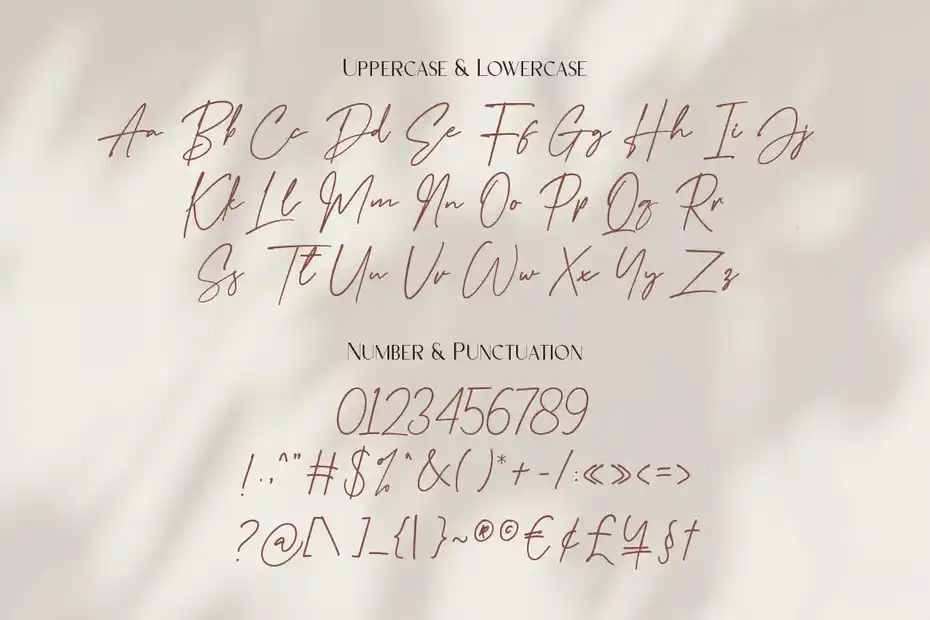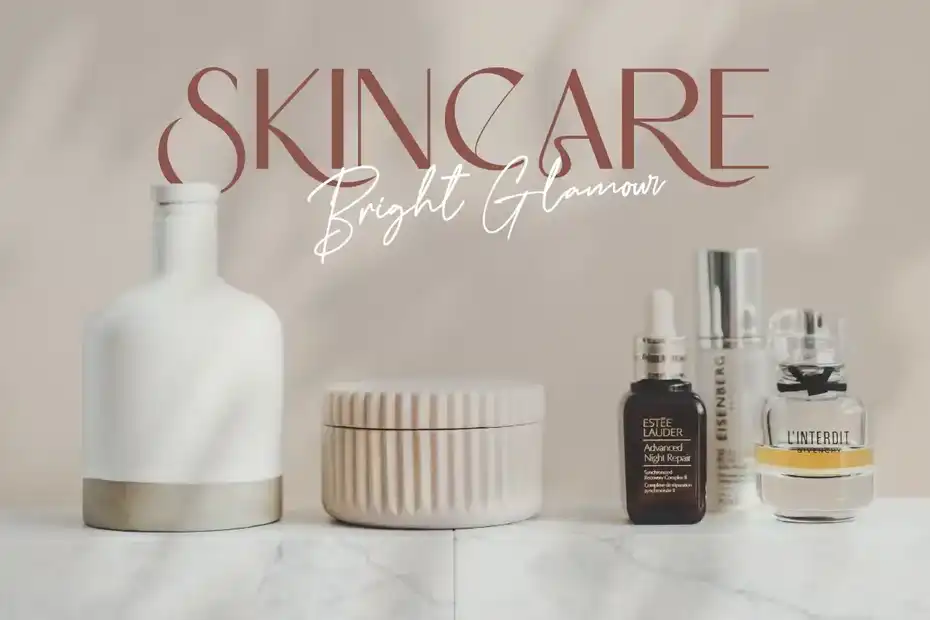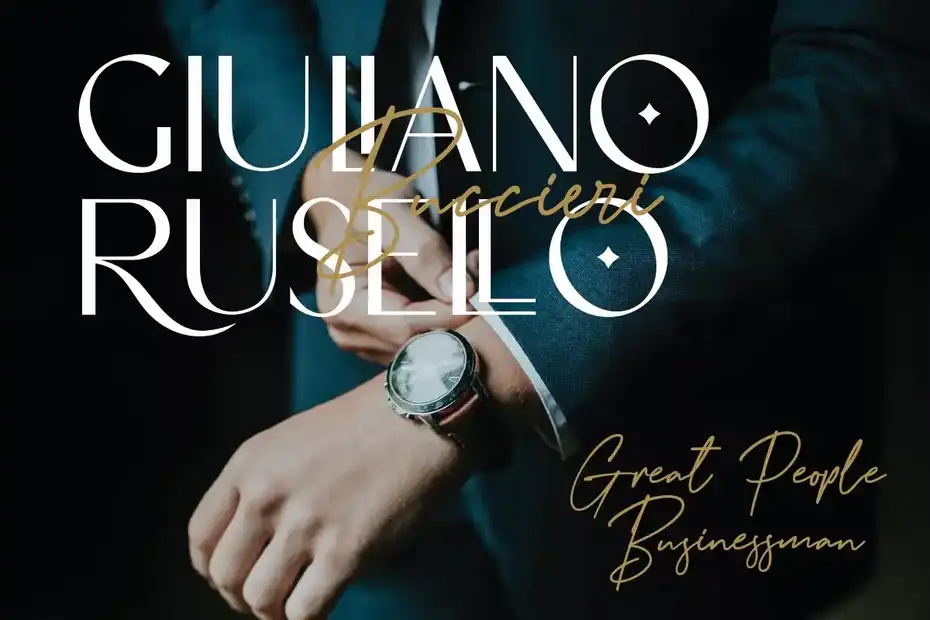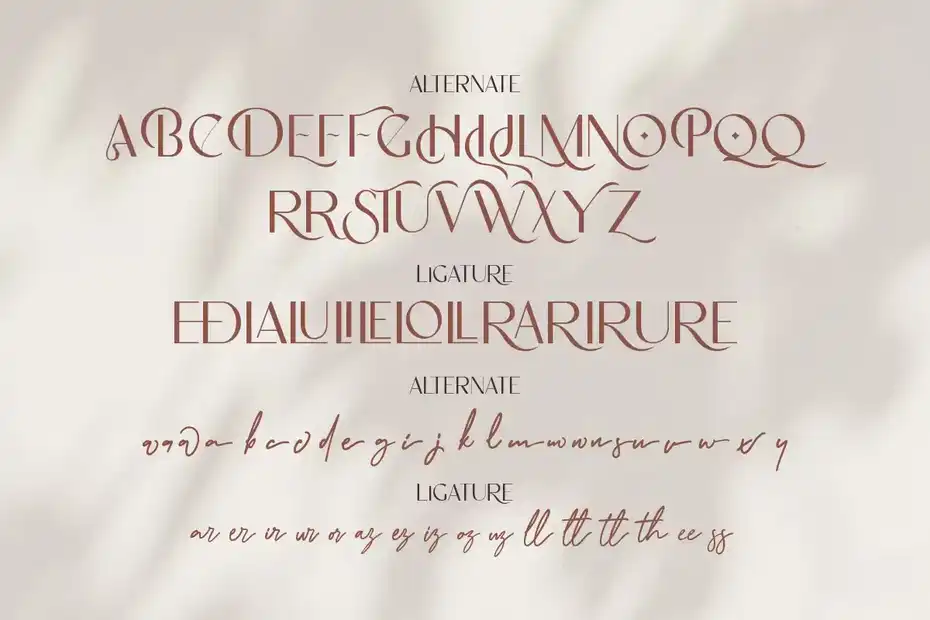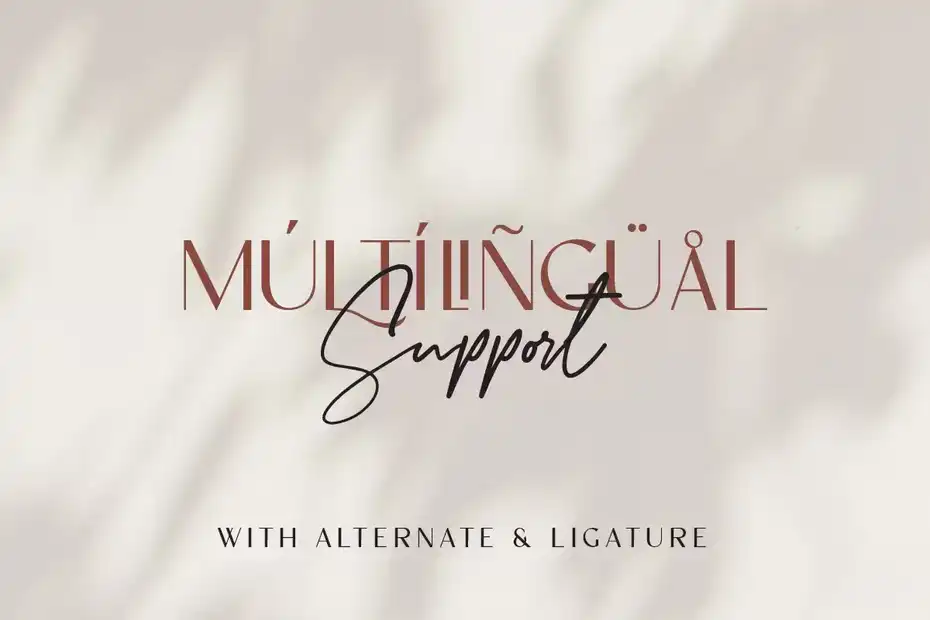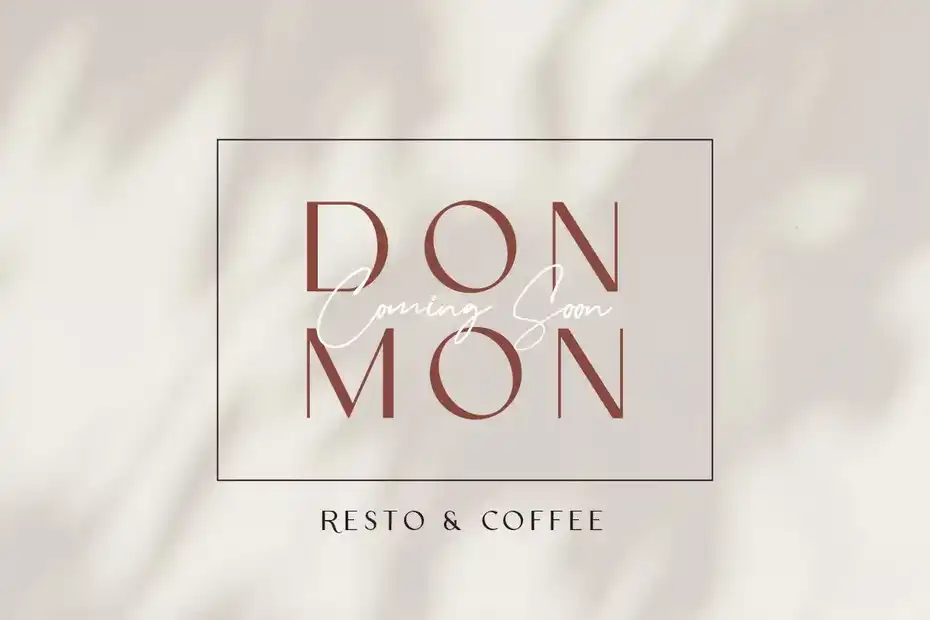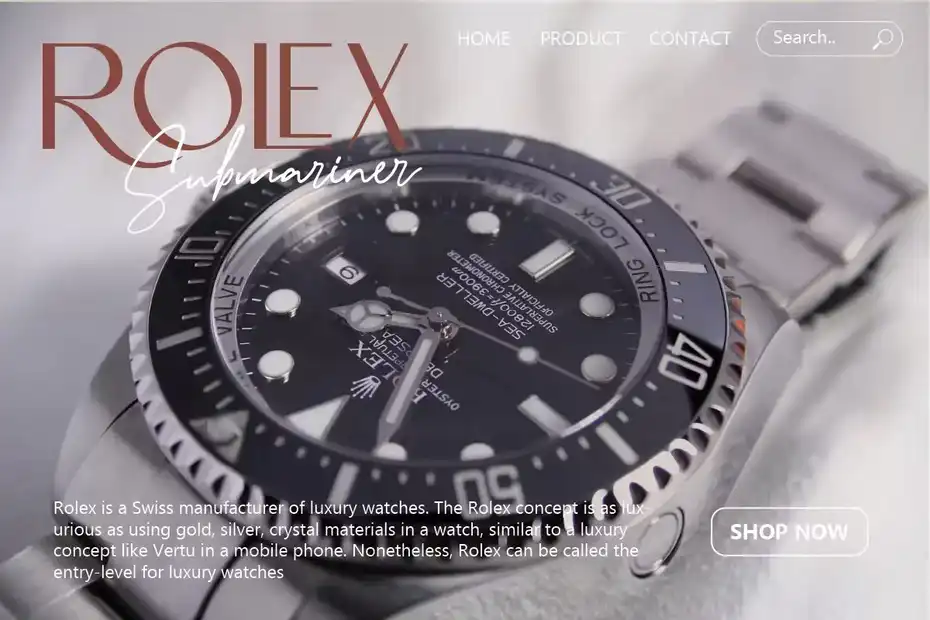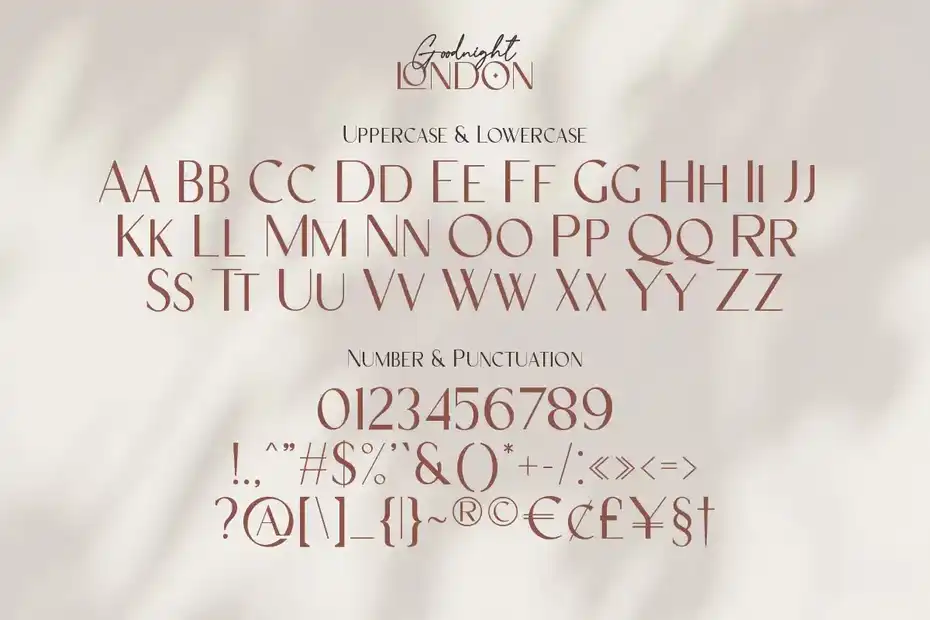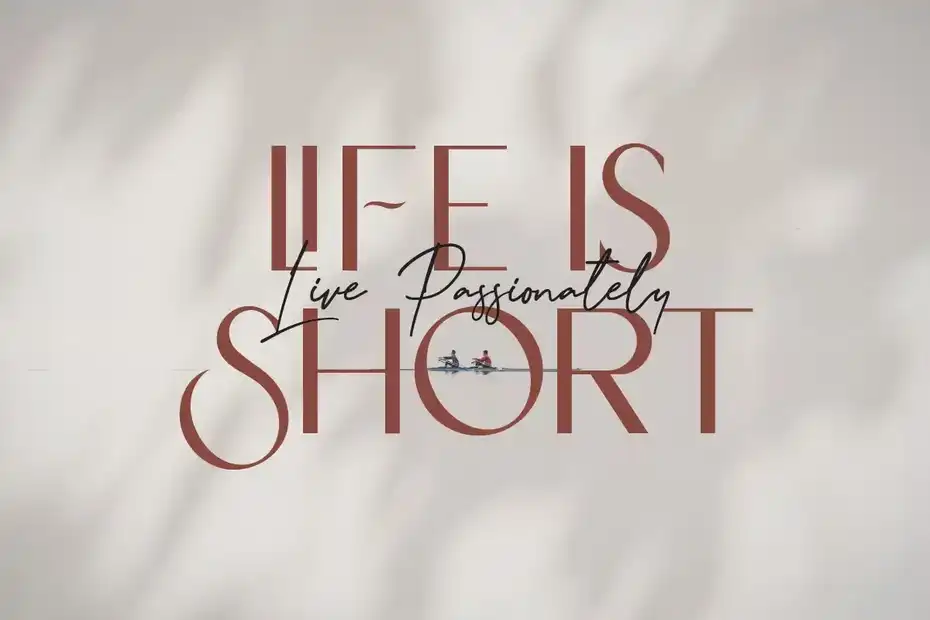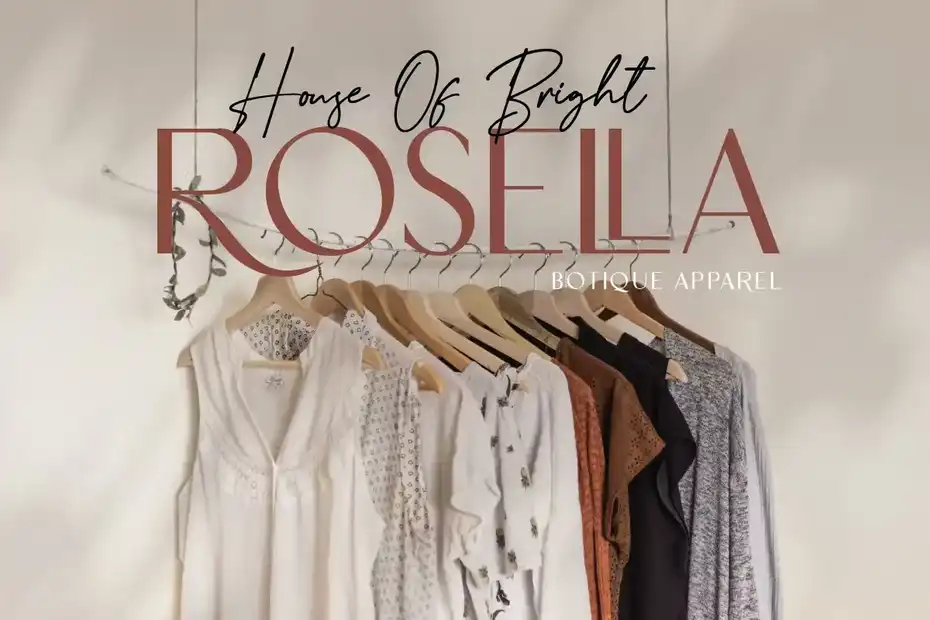
دانلود فونت انگلیسی Goodnight London – Font Duo
فونت انگلیسی Goodnight London – Font Duo : این مجموعه شامل یک فونت به سبک Sans-Serif است که برای لوگو، برندینگ، تبلیغات مسافرتی، پست شبکه های اجتماعی، طرح بندی مجلات، بسته‌ بندی محصول، نقل‌ قول‌ و پوشش متنی بر روی تصویر پس زمینه مناسب میباشد.